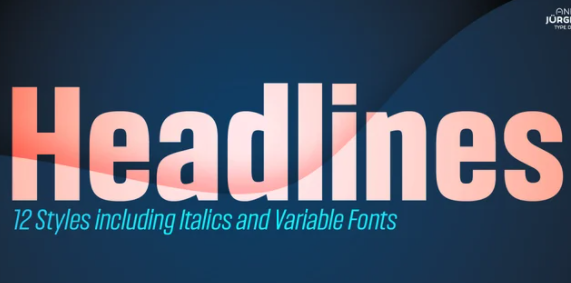
[Myfonts] Headlines Font (2021)
Семейство шрифтов Headlines было разработано для оптимизированной настройки заголовков.
Уплотненные буквы предназначены для четких и прямых заголовков, а также позволяют длинным словам и заголовкам найти пространство, необходимое для хорошо скомпонованного заголовка. Интересным плюсом этого шрифта являются его произвольные лигатуры. Семейство шрифтов Headlines содержит ряд специальных лигатур для определенных комбинаций, чтобы заполнить распространенные визуальные пробелы, такие как tty, rv и многие другие.